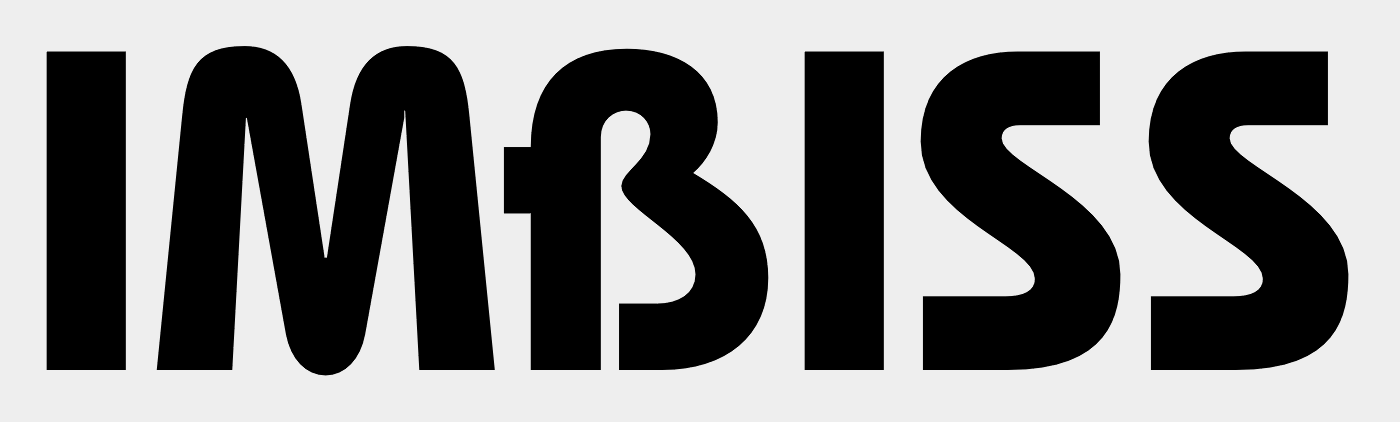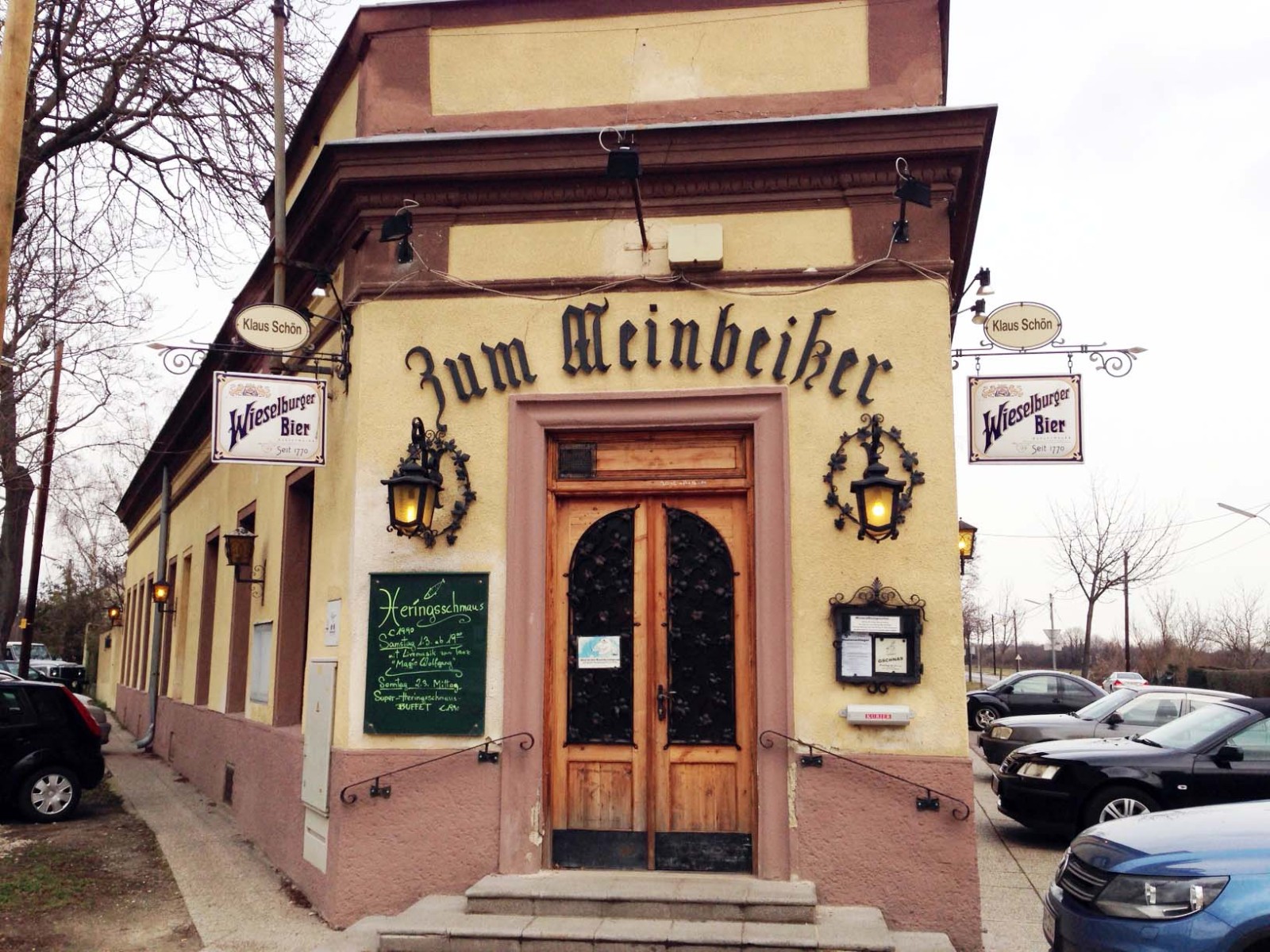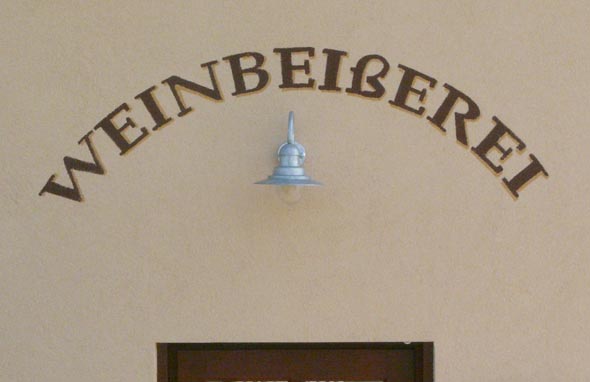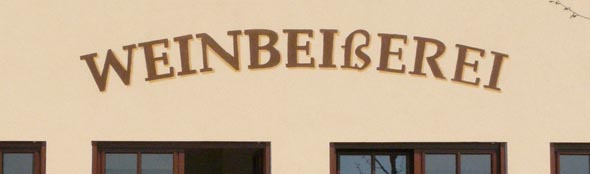
Es war denen offensichtlich schon irgendwie klar, daß ein ß in Imbiß gehört, sie konnten sich nur nicht mehr so recht entsinnen, wo.
tja, der gute ed benguiat hat der bauhaus seinerzeit kein ordentliches „B“ spendiert.
mit „ß“ würde es nämlich so aussehen:
Über oder übrig?
Über:Sie konnten es schon so lange nicht mehr sehen und waren nach der Rechtschreibreform froh, es endlich austauschen zu dürfen. Und genau dann ging das B kaputt und noch einen Buchstaben mehr konnten sie sich nicht leisten.  :neenee:
tja, der gute ed benguiat hat der bauhaus seinerzeit kein ordentliches „B“ spendiert.
mit „ß“ würde es nämlich so aussehen:
Ja, aber im Photo ist dieser Buchstabe ja auch noch etwas niedriger als die anderen, was den Eindruck noch verstärkt, daß da ein Fremdkörper in der Versalzeile sitzt (wiewohl mir ansonsten schon bewußt ist, daß ja eher die Versalien einenn Tick weniger Höhe haben sollten als die Minuskeln mit Oberlänge).
seit jahren fahre ich hier vorbei und werde den verdacht nicht los, dass der beliebte „Weinbeißer“ in wahrheit ein „Meinbeißer“ ist.
Eher ein Êeinbeißer â€¦ Das ß hängt auch zu hoch und ist vermutlich gefischt.
Kannst ja mal schauen, wie die reagieren, wenn Du sie darauf hinweist, dass da ein Buchstabe umgekippt ist.
… guck mal, Chef, solche gefrästen Buchstaben kann man jetzt auch im Internet bestellen, fix und fertig mit Abstandshaltern und Schrauben. Und dranschrauben kann das doch der Hausmeister, der ist doch sowieso nicht ausgelastet … :nicken:
Eindeutig kein M, sondern ein kopfstehendes W.
Wer beißt denn eigentlich Wein? Oder beißt vielmehr der Wein? In den Augen vielleicht oder zwickt er im Magen …? Oder am nächsten Morgen das Hirn …?  :-?
Wer beißt denn eigentlich Wein?
der duden sagt: anspruchsvoller, den Wein bewusst genießender Weintrinker und -kenner
Ich hab mir mal die Leiter geholt..
Wer beißt denn eigentlich Wein? Oder beißt vielmehr der Wein? In den Augen vielleicht oder zwickt er im Magen …? Oder am nächsten Morgen das Hirn …?  :-?
Wie auch immer, das Phänomen scheint verbreiteter als man denkt und auch immer mit typographischen Auffälligkeiten verbunden: